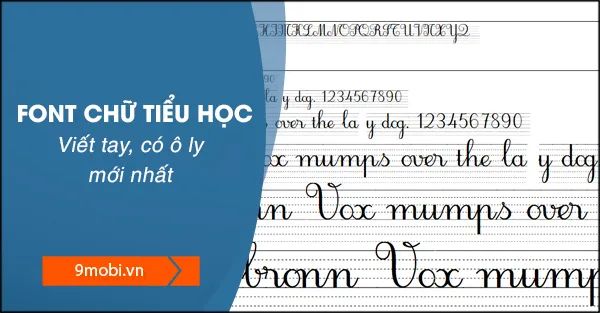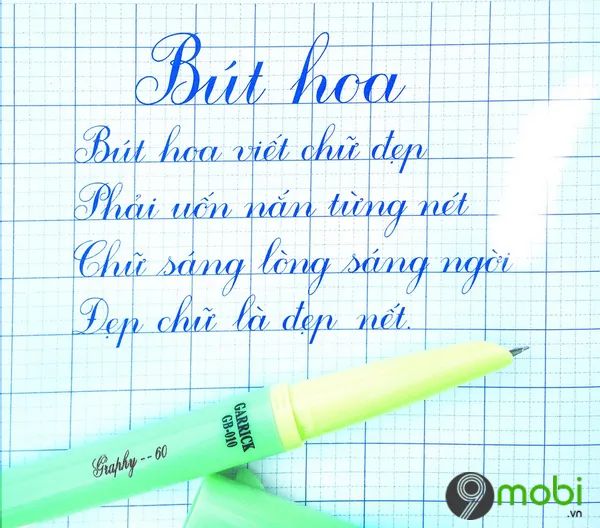
Tải bộ font chữ tiểu học chuẩn HP001, với ô ly và kiểu chữ nét thanh nét đậm.
Font chữ tiểu học (như HP001, HP0015HN,...) là bộ font chữ tiếng Việt được thầy cô, phụ huynh và học sinh yêu thích, giúp cải thiện kỹ năng viết chữ đẹp. Dưới đây là các mẫu font chữ tiểu học chuẩn mới nhất theo quy chuẩn của Bộ Giáo dục & Đào tạo, mời bạn tham khảo và tải về.
1. Font chữ tiểu học nét thanh nét đậm
Font chữ tiểu học với nét thanh nét đậm mang lại sự rõ ràng và dễ đọc, thích hợp cho các tài liệu giáo dục, sách truyện, truyện tranh, và sách thiếu nhi. Đây là công cụ hữu ích để trẻ em rèn luyện khả năng đọc hiểu và phát triển kỹ năng viết.
2. Font chữ tiểu học có ô ly, mẫu tập tô
Mẫu chữ tập tô với nét đứt được thiết kế trên vở kẻ 4 ly giúp học sinh làm quen với cách viết chữ chuẩn, theo kích thước chuẩn xác. Tải font chữ tiểu học HP001 sẽ giúp các em cải thiện chữ viết đẹp và viết gọn gàng hơn.
Bộ font chữ tiểu học bao gồm 19 font chữ viết tay, với nét thanh nét đậm chuẩn theo tiêu chuẩn của Bộ Giáo dục & Đào tạo, dung lượng nhẹ, lý tưởng để học sinh lớp 1 đến lớp 5 luyện viết chữ đẹp.